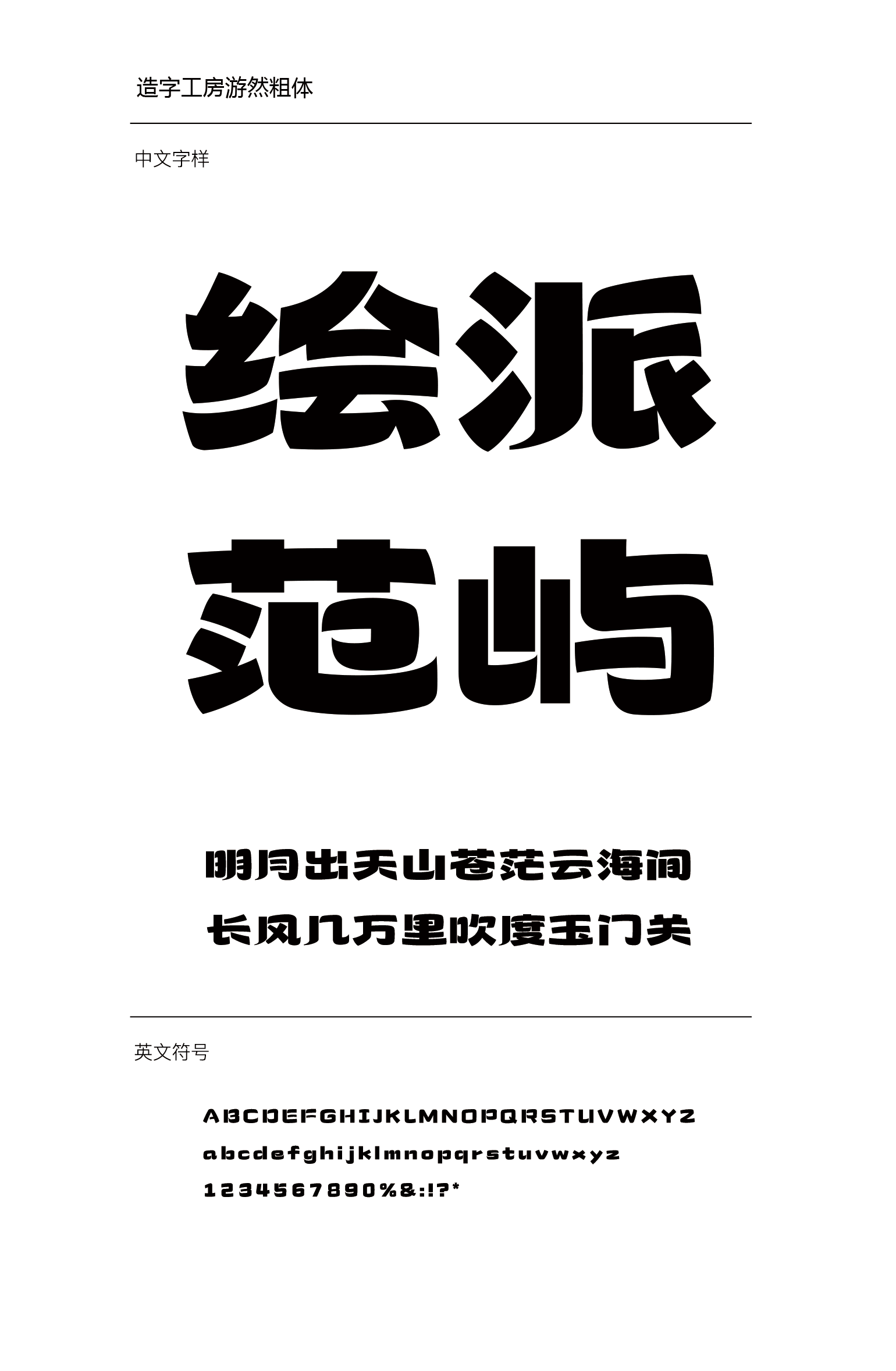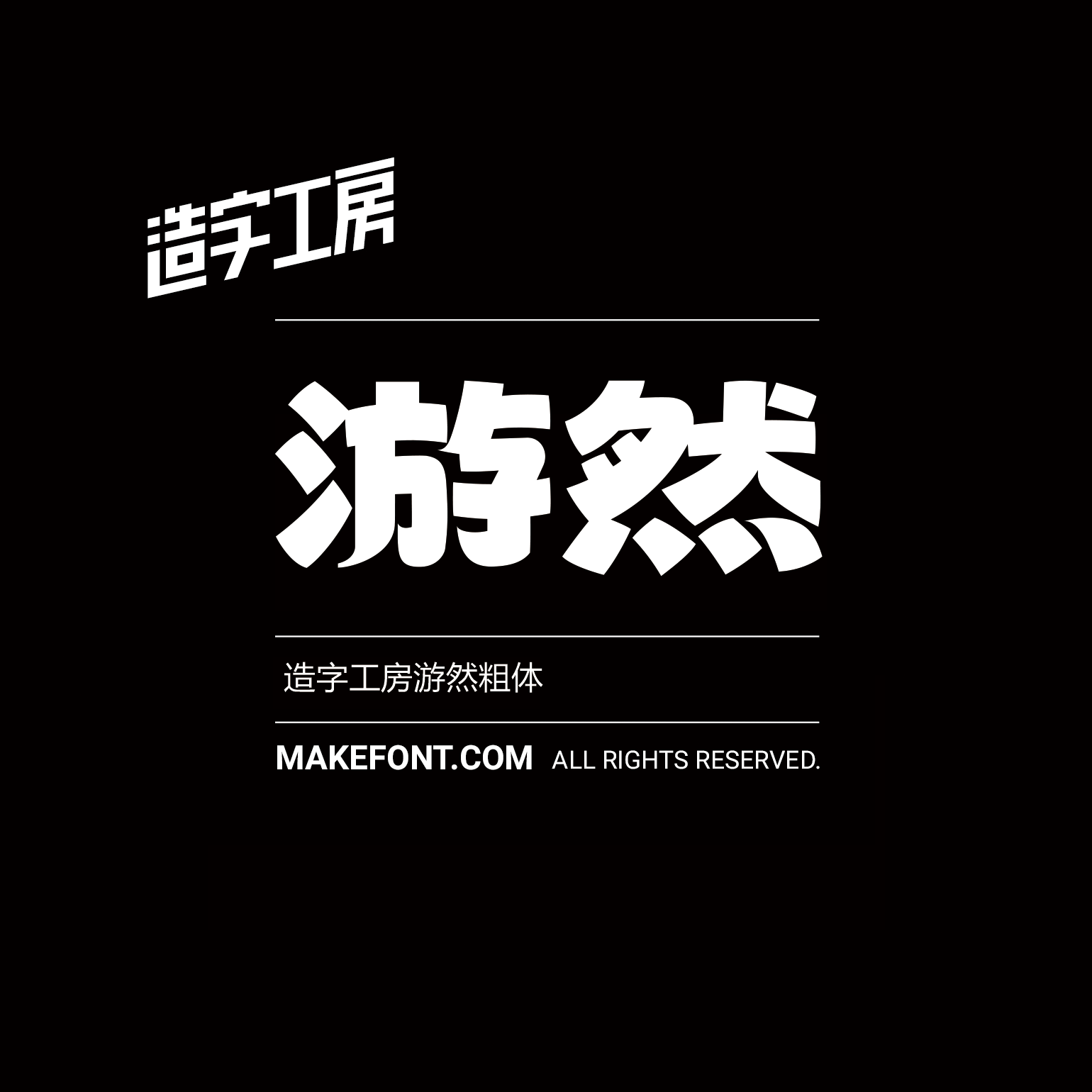
造字工房游然粗体设计说明
造字工房游然体系列,字形扁宽、饱满圆润,豁达舒展却不浮夸,笔画连接处断笔不断形的处理方式,深谙传统书法笔意,上下笔画圆弧对称的设计给字体增添了一种特有的艺术美感,整体风格舒展挺劲,看似信笔挥洒,意忘工拙,可又姿态百出,天真浪漫,气象雍容,自出新意。适用于艺术作品,平面海报,广告设计推广等环境。本字体为简体字库,采用OpenType/CID格式,Adobe-GB1-5编码。基于中华人民共和国GB2312-80字符集标准,另按需添加101个汉字。共收容字数6864CJK汉字,ASCII常用字符100个。